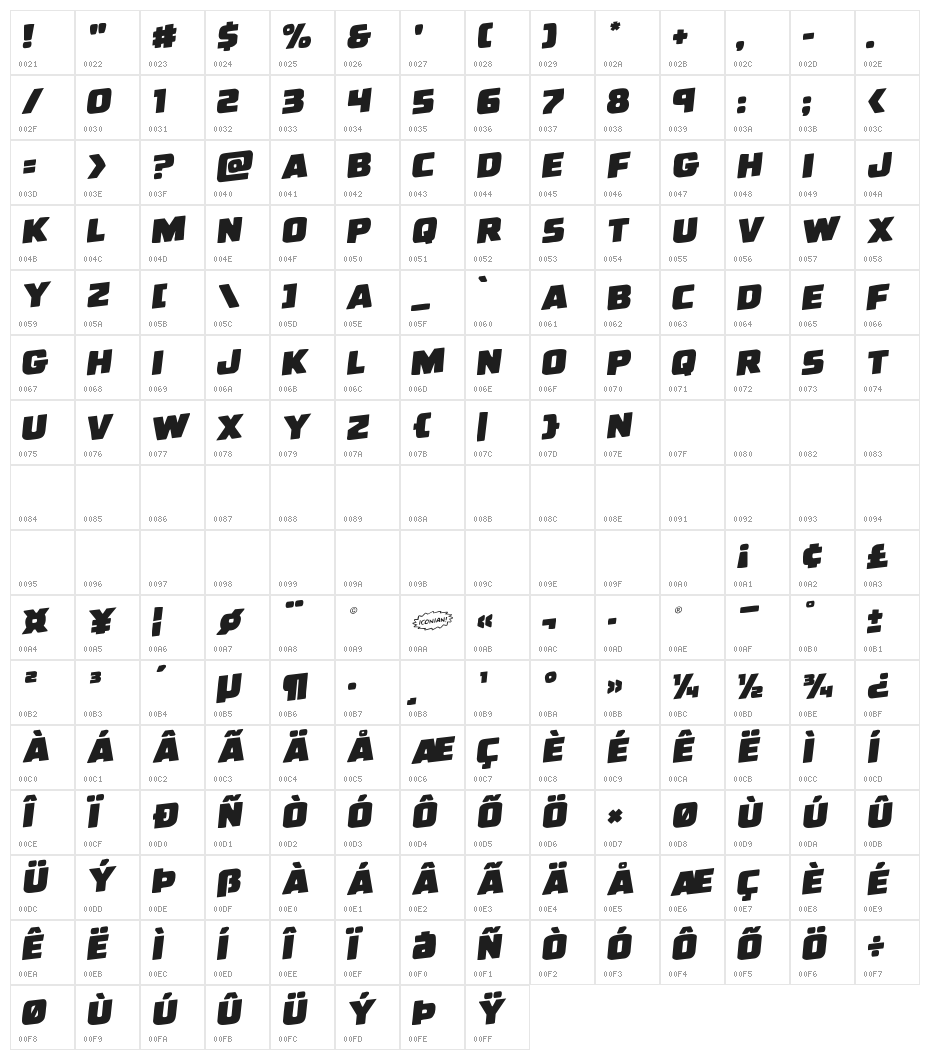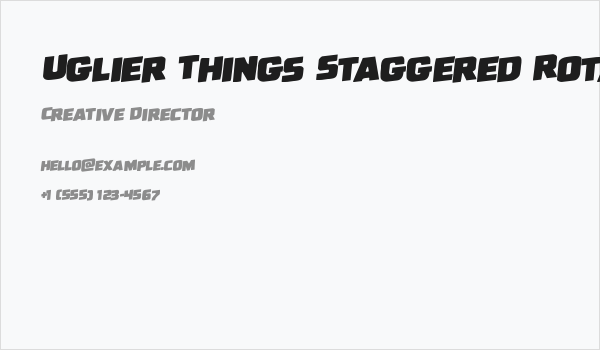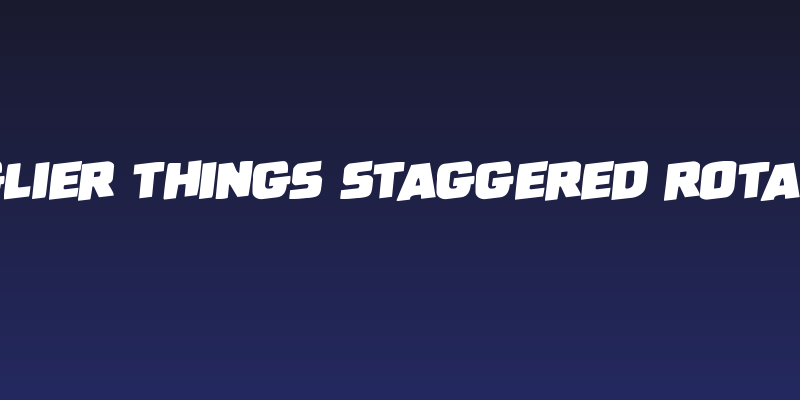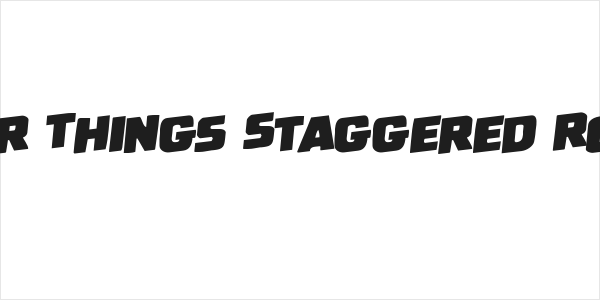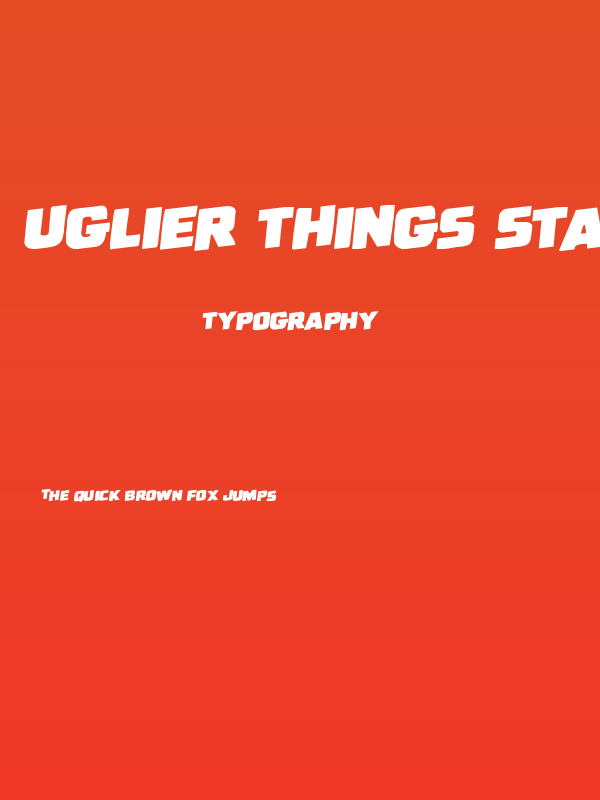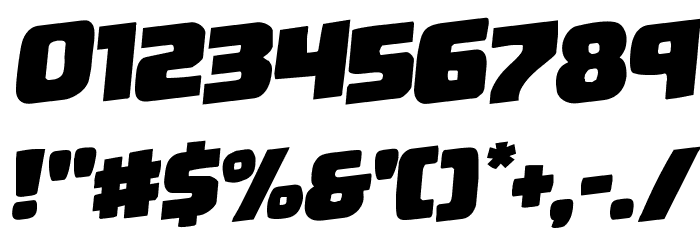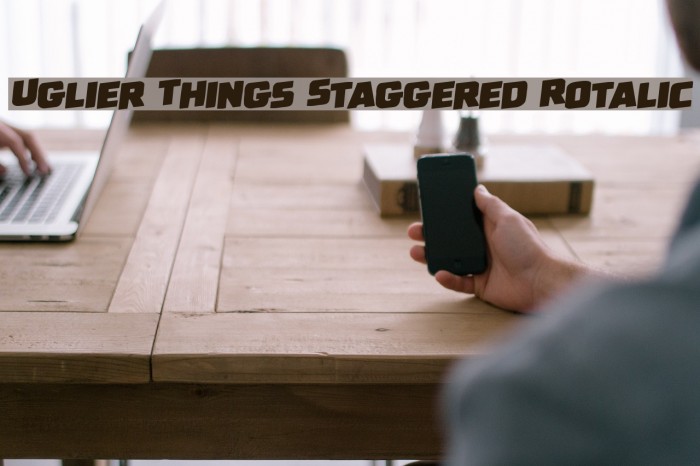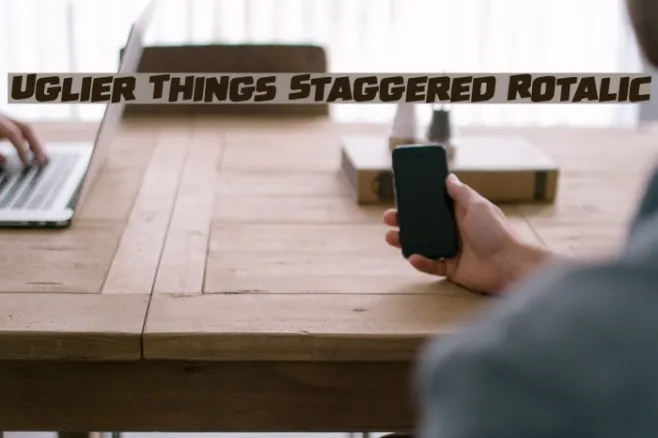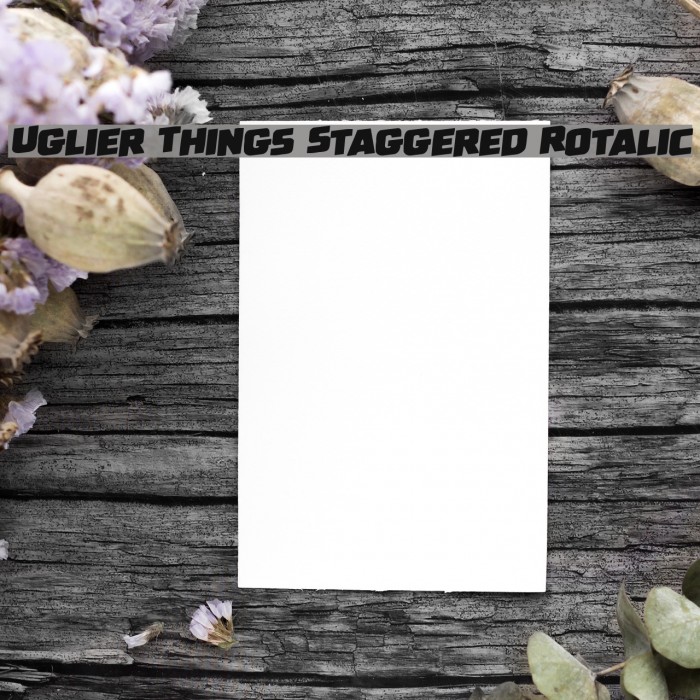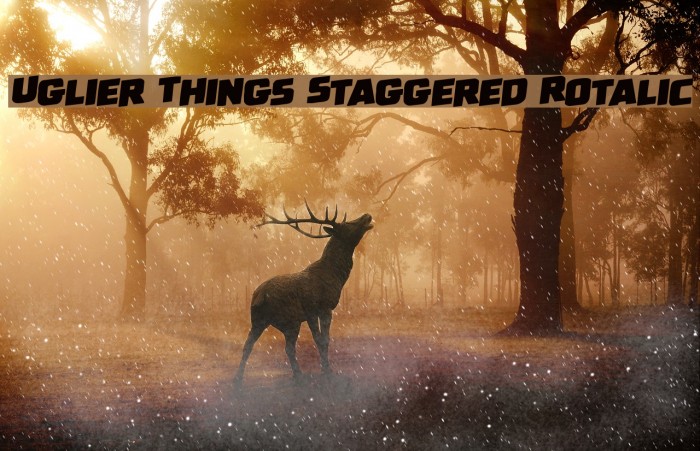
Uglier Things Staggered Rotalic Font
| Vorgeschlagene Projekte | Ideal for sports branding, dynamic posters, bold advertising campaigns, and eye-catching headlines. |